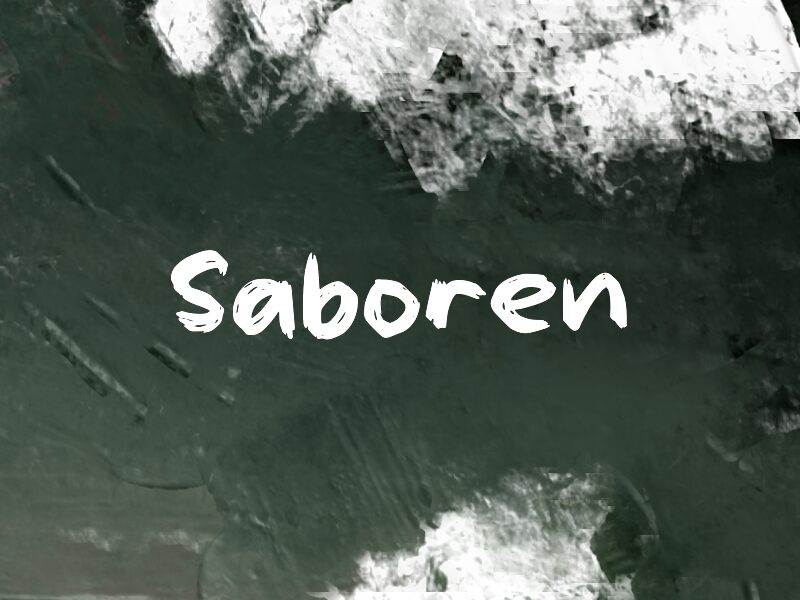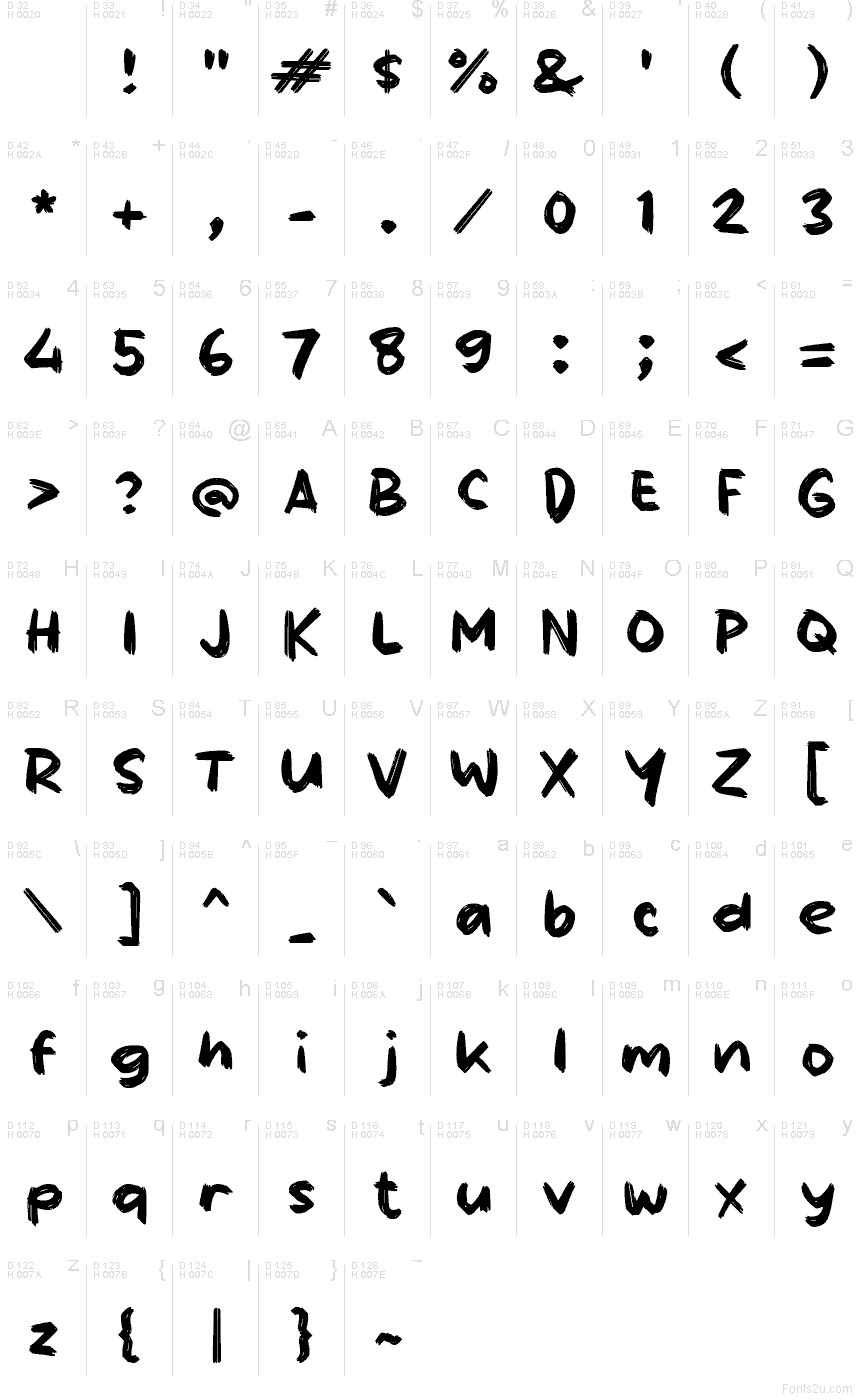
Saboren
Saboren da Wep é uma fonte estilo pincel gratuita, formada por traços amplos, formas arredondadas e bordas rústicas que conferem movimento às letras. A textura parece orgânica e desigual em vez de polida, com interiores riscados e pontas afiladas que fazem o design parecer uma escrita rápida à mão, e não um script perfeitamente editado.
Isso torna a Saboren uma escolha natural para cartazes de música, gráficos de streetwear, embalagens, banners sociais e títulos curtos, onde a superfície pintada à mão é tão importante quanto a própria palavra. O ritmo irregular e o acabamento de pincel seco conferem aos flyers de eventos e miniaturas de vídeo uma presença mais marcante e imediata do que uma fonte de pincel mais suave permitiria.